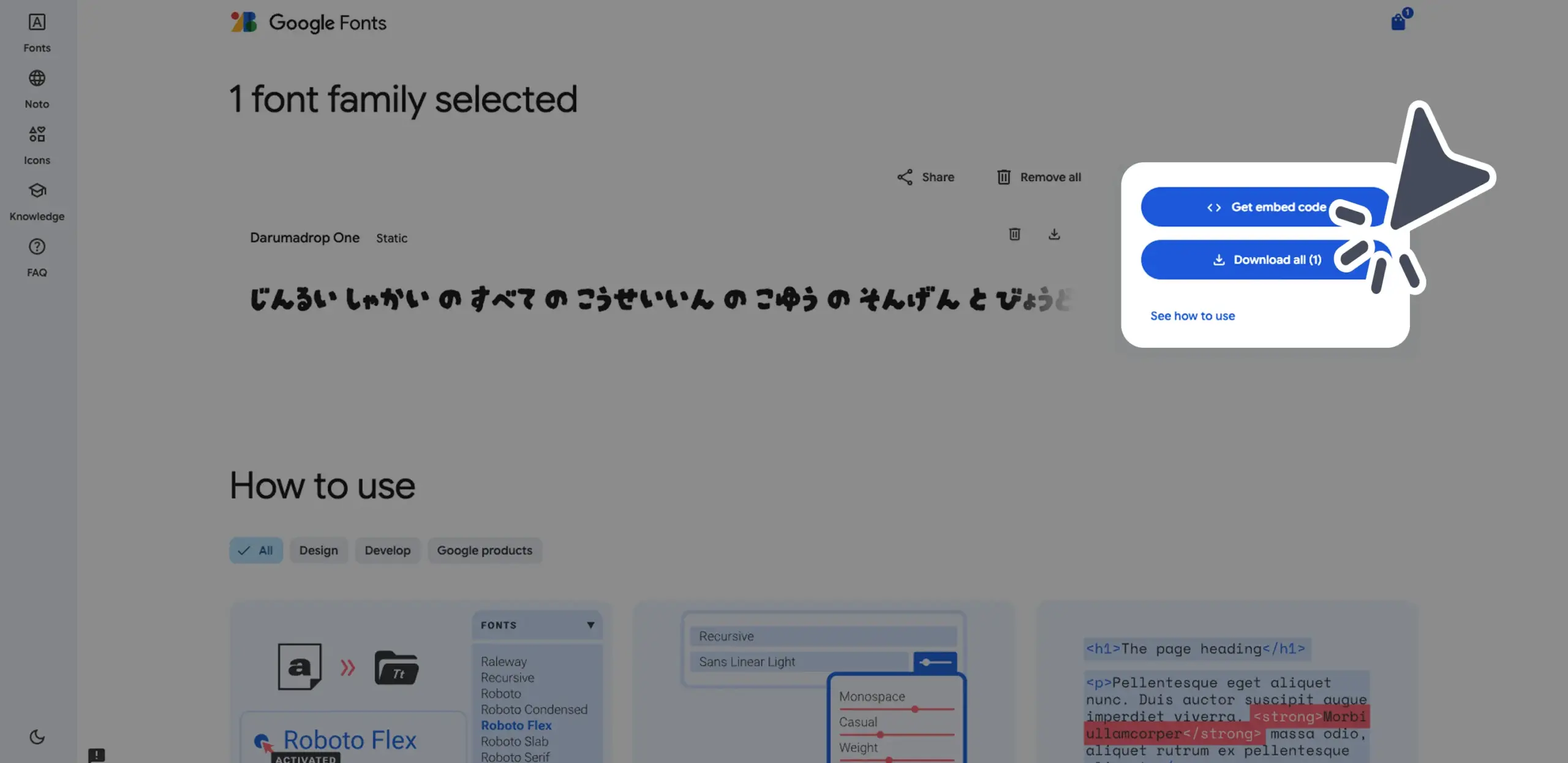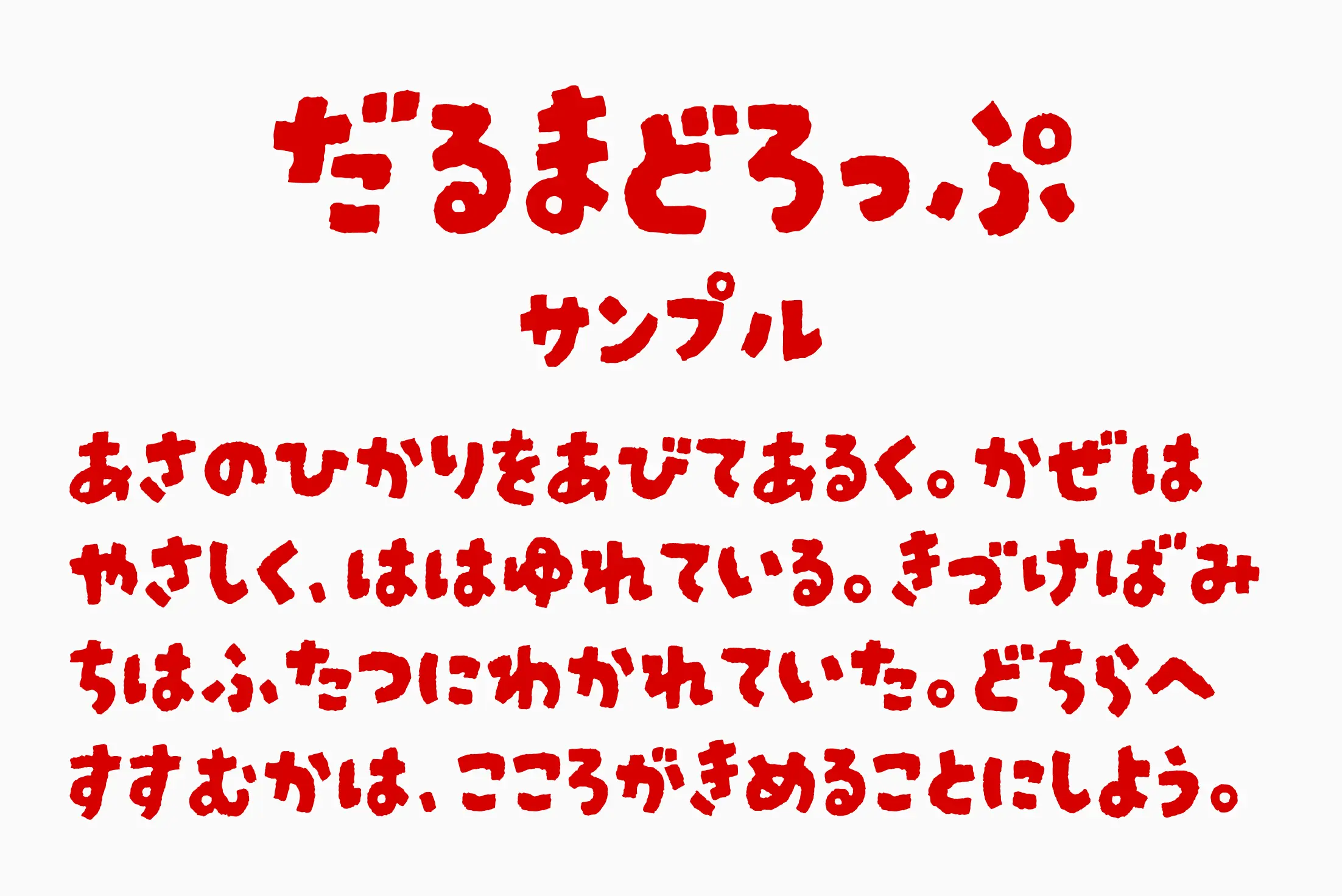
だるまどろっぷ
だるま落としからヒントを得た、日本の文化を感じさせる手描き風ディスプレイフォントです。濃厚な筆の質感とポップな丸みが融合し、「昭和」「和」「伝統工芸」の魅力をモダンに表現しています。ジブリ風のやわらかいタイトルや、同人誌・POP・パッケージなど、和の雰囲気を遊び心と一緒に演出したい場面にぴったりです。